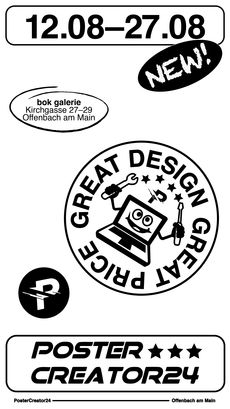
Typografie/Type Design (Typografie)
Die beiden Bereiche des Lehrgebiets bedingen sich gegenseitig, denn Typografie kann nicht ohne Type Design entstehen, und Type Design entfaltet erst in der typografischen Interpretation seine volle Wirkung.
Typografie organisiert, vermittelt und konnotiert sprachlich-visuelle Inhalte zu einem sinnstiftenden Bedeutungsgewinn. Sie kann eine Aussage unterstützen, hinterfragen, undeutlich machen, schönen oder auch vereinfachen; damit ist sie ein mächtiges und gleichsam manipulatives Werkzeug. Sie bewegt sich innerhalb der folgenden Dimensionen in einer kunstvollen Verschränkung: in der geschichtlich-theoretischen, der handwerklichen und der gestalterischen. Als kulturelle Praxis ist sie bei aller unabdingbarer, historischer Konvention im Hinblick auf technische und gesellschaftliche Bedingungen stets im Wandel und somit ein Kommentar auf die Gegenwart.
Im Studium werden die vielfältigen Anwendungsgebiete im analogen wie digitalen Spektrum – von Buchgestaltung, über Akzidenzen, Erscheinungsbilder, digitale/interaktive Medien wie Websites, Informationsgestaltung, Ausstellungsgestaltung, Typografie im Raum bis hin zu bewegter Typografie – erprobt. Ein jedes erfordert ganz unterschiedliche typografisch-syntaktische Funktionsweisen, die es zu hinterfragen, erlernen, bedienen und weiterzuentwickeln gilt. Einhergehend mit der praktischen Projektarbeit werden Kenntnisse in Mikro- und Makrotypografie, Typografie- und Schriftgeschichte, Schriftklassifikation, -wahl und -wirkung, Druck- und Herstellungsverfahren erarbeitet. Neben dem Überprüfen überlieferter Regeln sollen eigene geschaffen und Raum für Experiment und Prozess genutzt werden. Frei nach Kurt Schwitters Diktum von 1924 »Typographie kann unter Umständen Kunst sein« soll die Grenze von angewandt und autonom im Fach Typografie ausgelotet werden. Es wird eine künstlerische Autor_innenschaft im Sinne von eigener Form- und Inhaltsproduktion gefördert.
Im Type Design, dem Gestalten von Buchstaben zu einer Schrift, offenbart sich eine persönliche Handschrift und kulturelle Prägung. Die Disziplin besteht aus diesem kreativ-schöpferischen Teil mit unendlichen Ausdrucksmöglichkeiten und aus einem pragmatisch-technischen Teil.
Das Studium ist geprägt vom Zeichnen/Schreiben/Bauen, von Detailbetrachtungen zu Proportionen, Gewicht, Kontrast und Rhythmus, vom Denken in Systemen, von geschichtlichem Wissen sowie vom Umgang mit Technologie. Es können Schriftentwürfe von ganz unterschiedlicher Ausrichtung und Vertiefung verfolgt werden: modulare Schriften für plakative Anwendungen, Superfamilies für den Mengensatz, historische Revivals oder auch eine freie Organisation von Zeichen. Ferner kann die Idee der konzeptionellen Custom Type im Hinblick auf Erscheinungsbilder oder das eigene künstlerische Schaffen die Brücke zur Anwendung schlagen, denn die Verknüpfung beider Bereiche ist ausdrücklich erwünscht. Type Design wird primär im Hinblick auf das lateinische Alphabet vermittelt, andere Schriftsysteme können durchaus zum Gegenstand der Betrachtung werden. Die Nähe der HfG Offenbach zum Klingspor Museum ermöglicht vertiefende Recherchen und evoziert spannende Begegnungen von Vergangenheit und Zeitgeist.